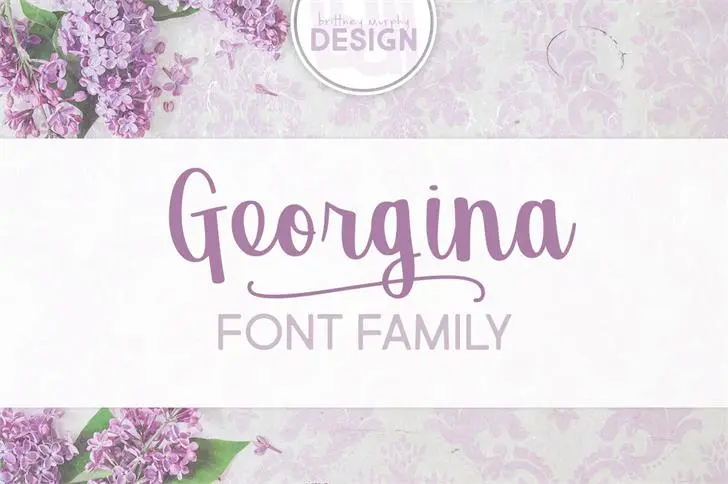
Georgina Script Font – Download Grátis
A Geórgia é uma cromática e charmosa fonte de escrita script que irá transformar seu design em algo verdadeiramente especial. Esta família de fontes inclui não só a versão grossa, mas também uma versão mais fina e leve, adequada para um uso pessoal sem custo adicional. Brittney Murphy Design criou este trabalho artístico, disponível gratuitamente para uso pessoal apenas. Para obter permissões comerciais, por favor visite http://brittneymurphydesign.com/downloads/georgina-font-family/ e faça seu pagamento. A Geórgia é uma opção incrível para aqueles que desejam transmitir a sua mensagem de forma única e imponente. Seja em cartazes, materiais promocionais ou design gráfico, ela oferece um toque encantador e elegante ao seu trabalho final. Além disso, os designers têm acesso a uma versão mais fina da fonte para aqueles que desejam adicionar um toque de sofisticação em textos interiores, sem comprometer o charme do design.